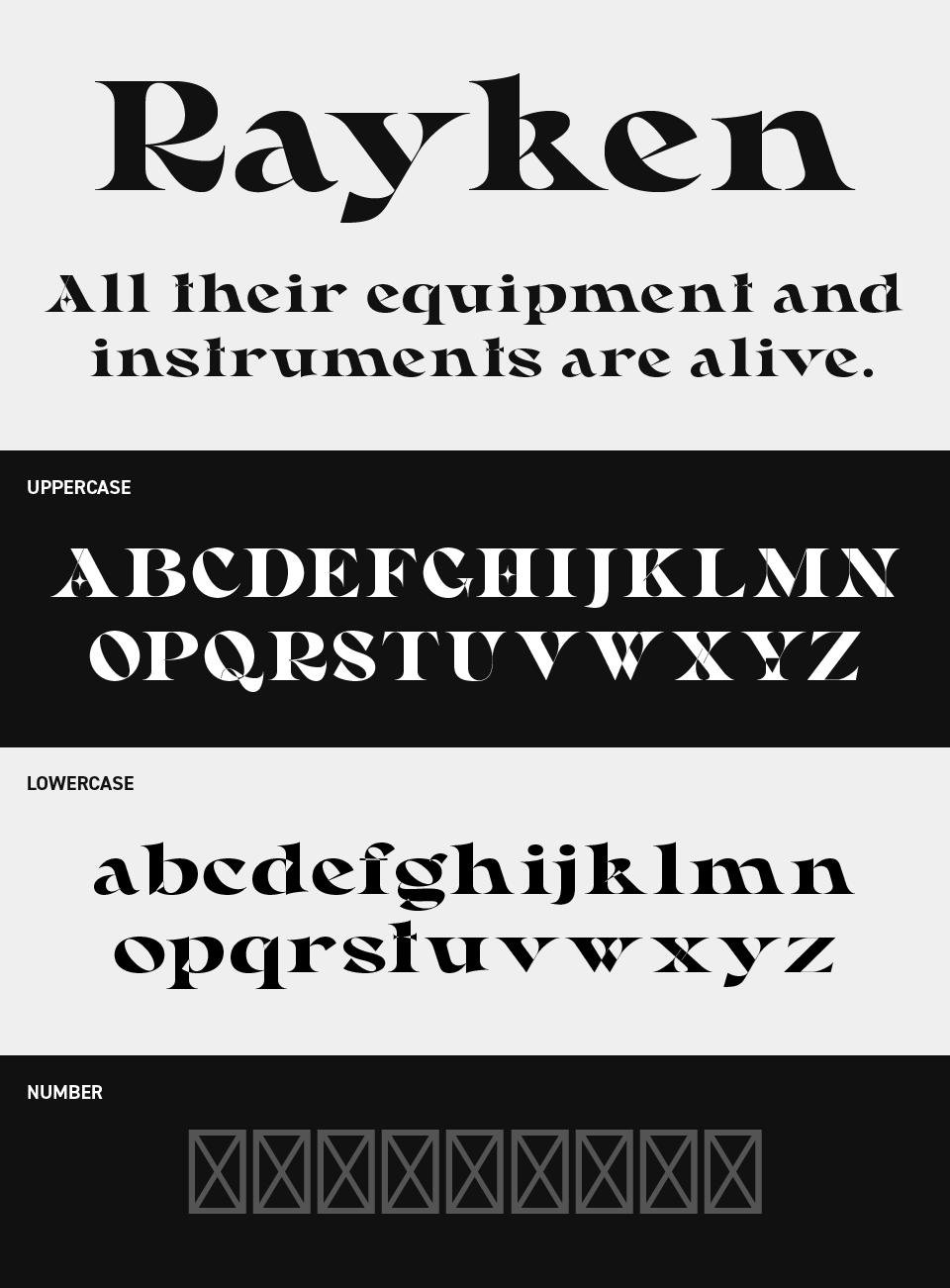
Raykenフォントは、鋭さとやわらかさを両立させたような、クラシカルでありながらエッジのきいたデザインセリフ体です。
斜めに走る切り口がまるで光を反射するように輝き、強さの中に色気が漂うデザインです。
どっしりとした重厚感がある一方で、文字のディテールに繊細な遊びが効いており、ラグジュアリーな印象やモダンなエレガンスを演出したいときにぴったりなフォントです。